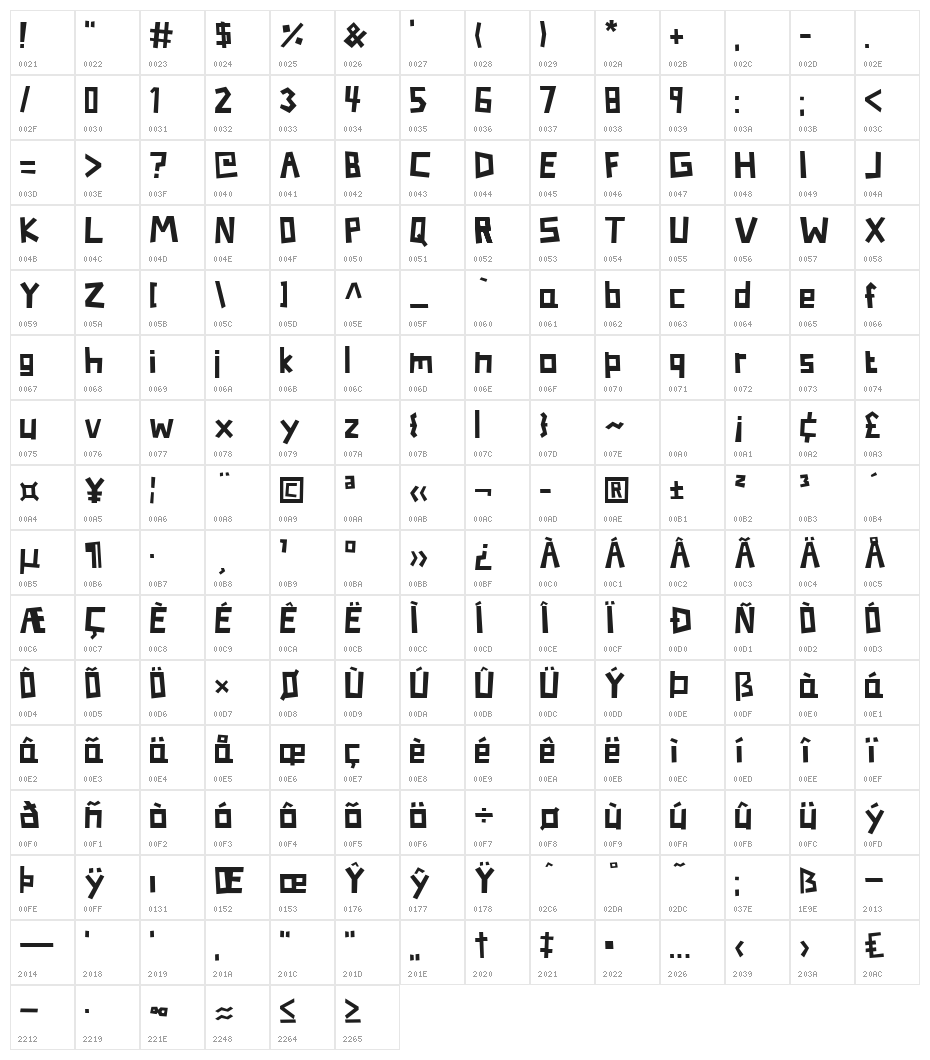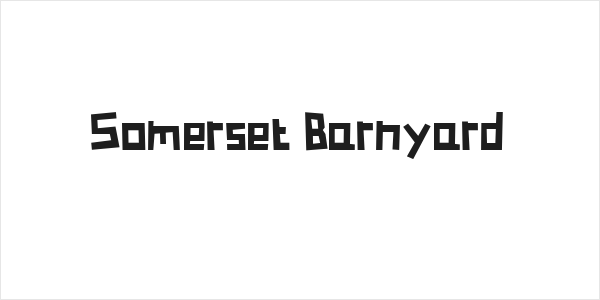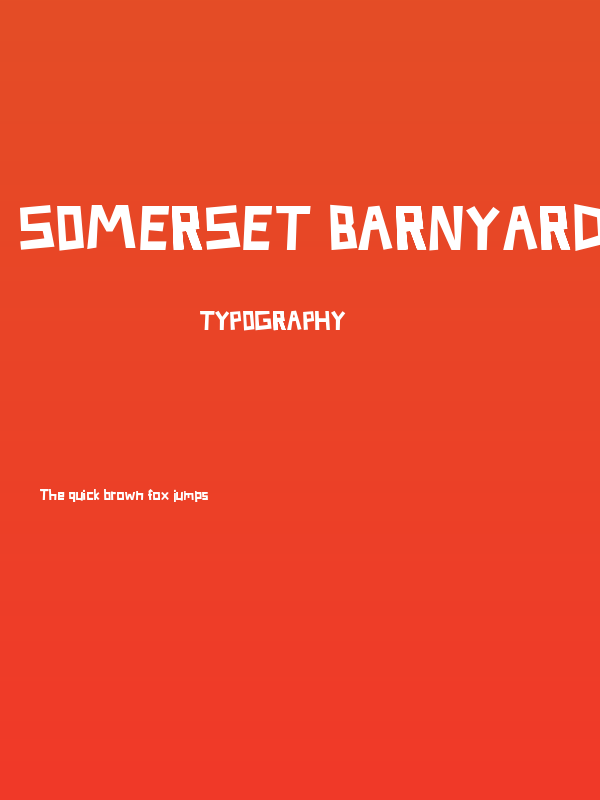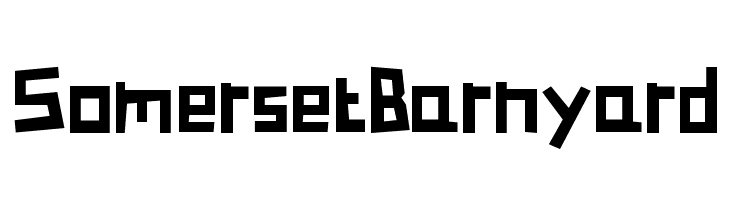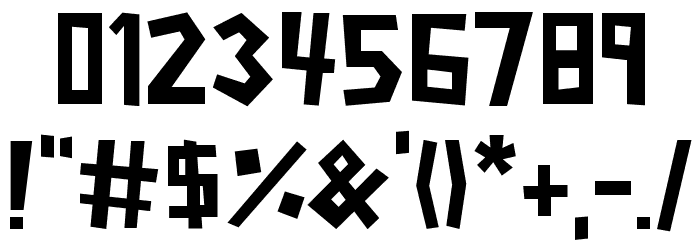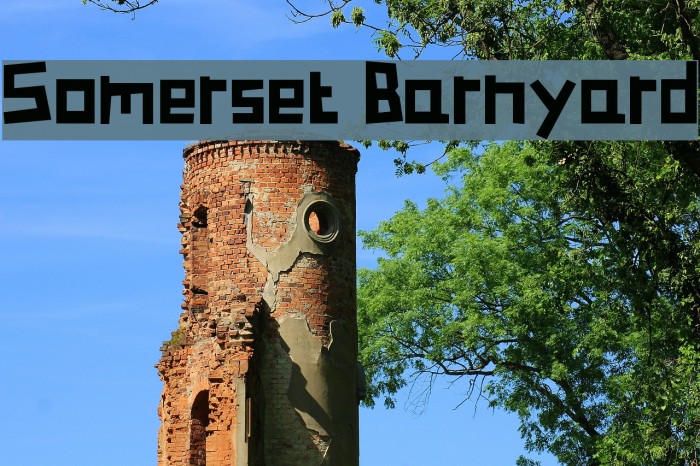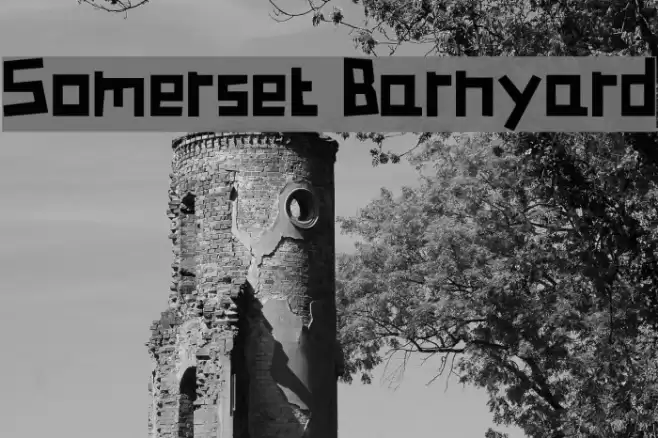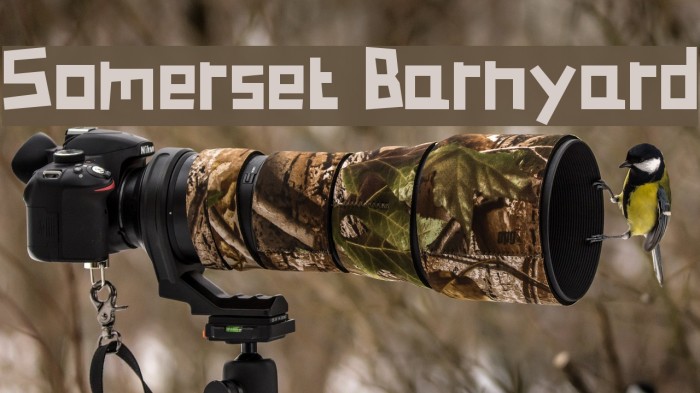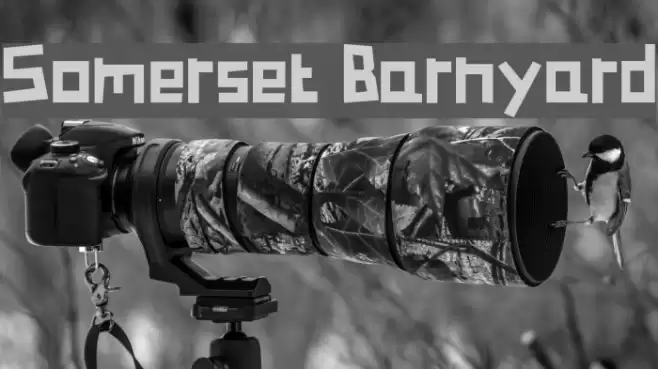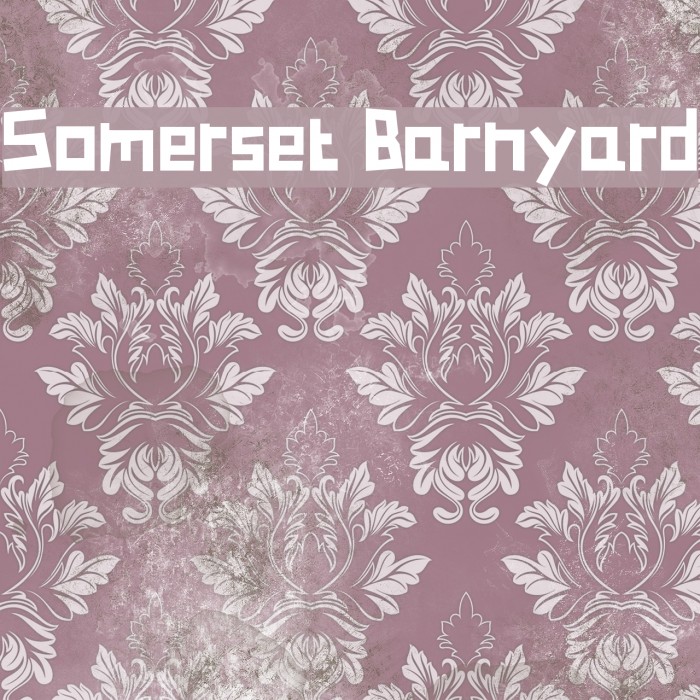
Somerset Barnyard Font
| Estilo general | Playful, Quirky, Energetic |
| Caso de uso | Headlines, Posters, Branding |
| Proyectos propuestos | Ideal for children's books, playful branding, event posters, and creative social media graphics. |